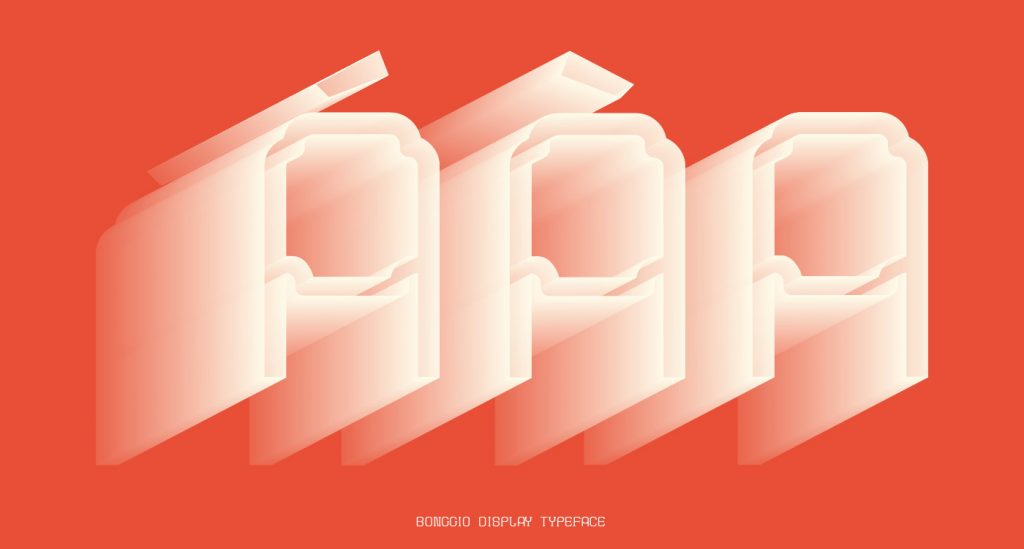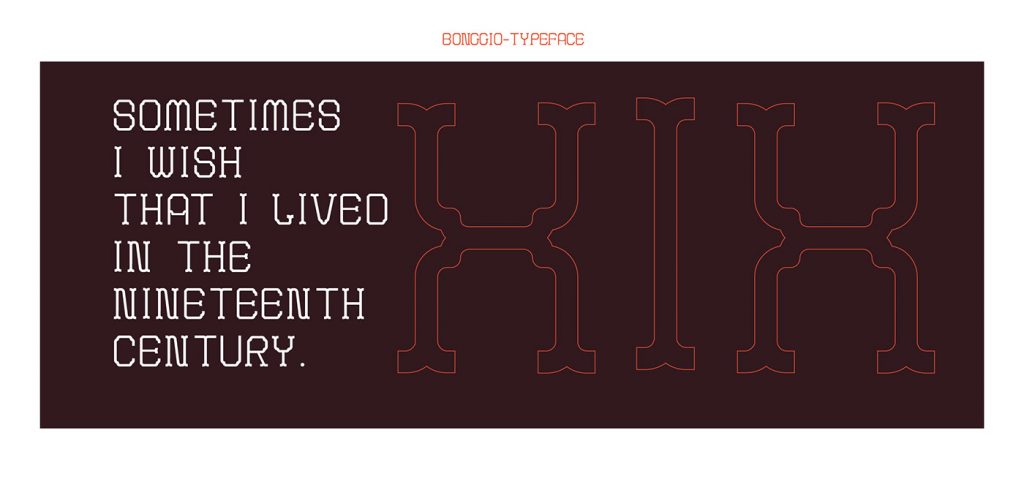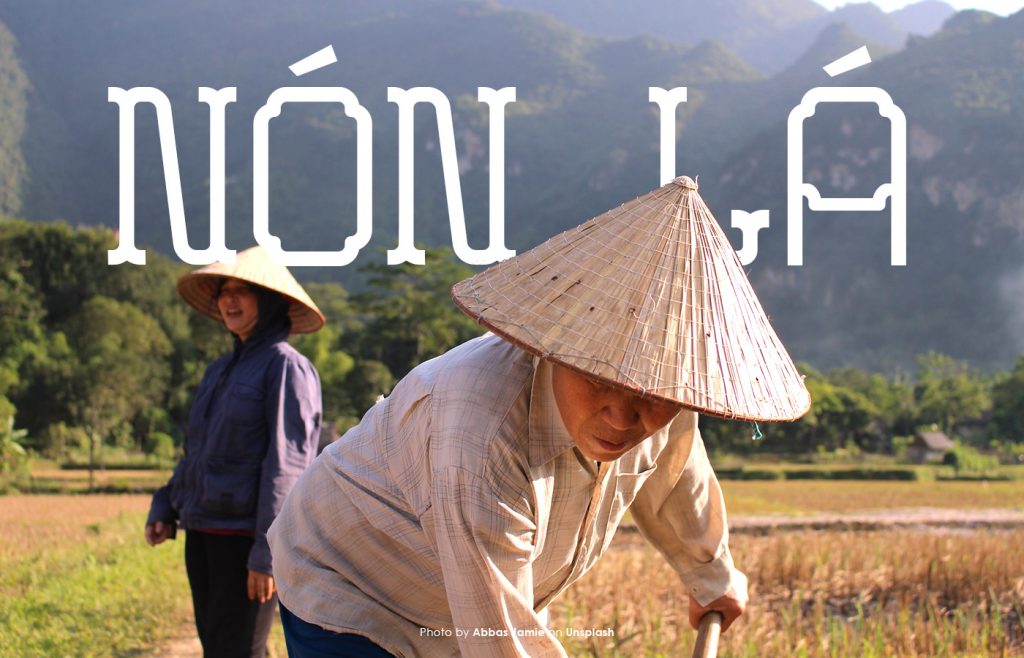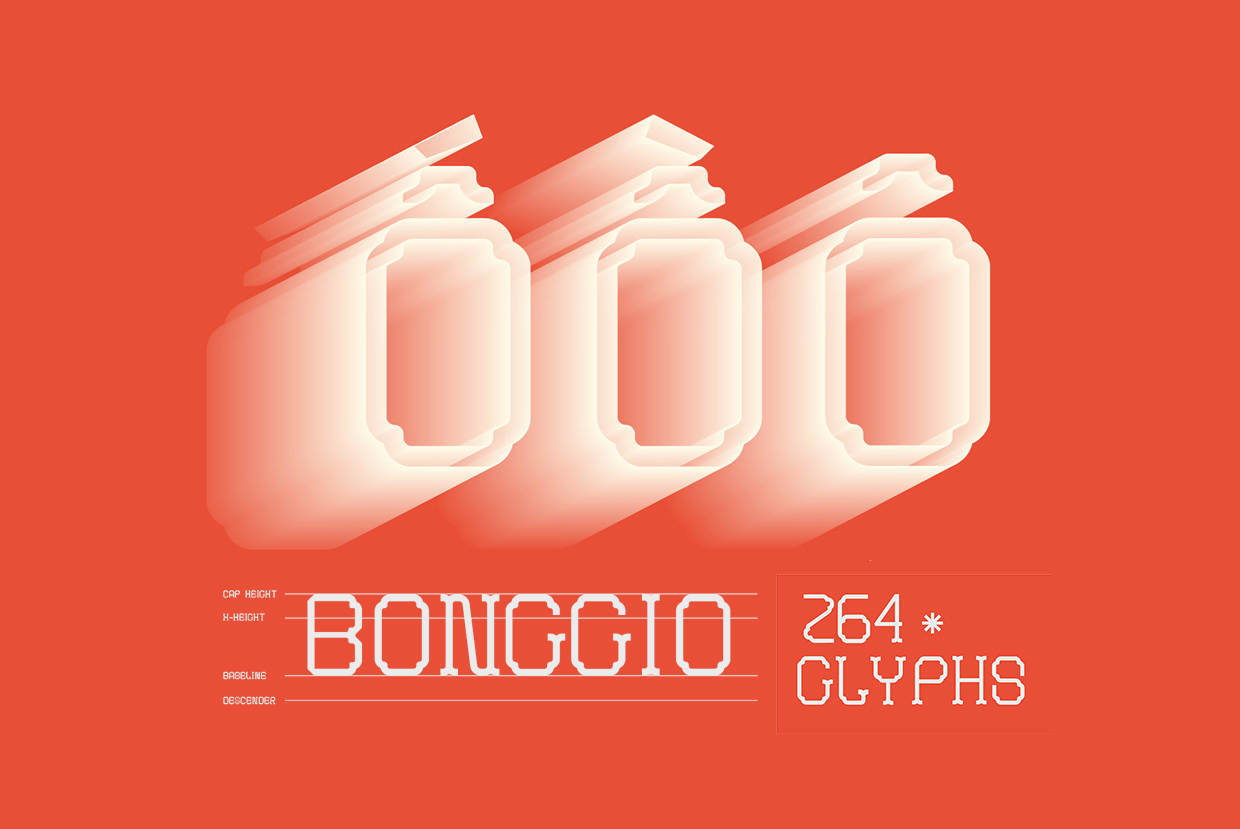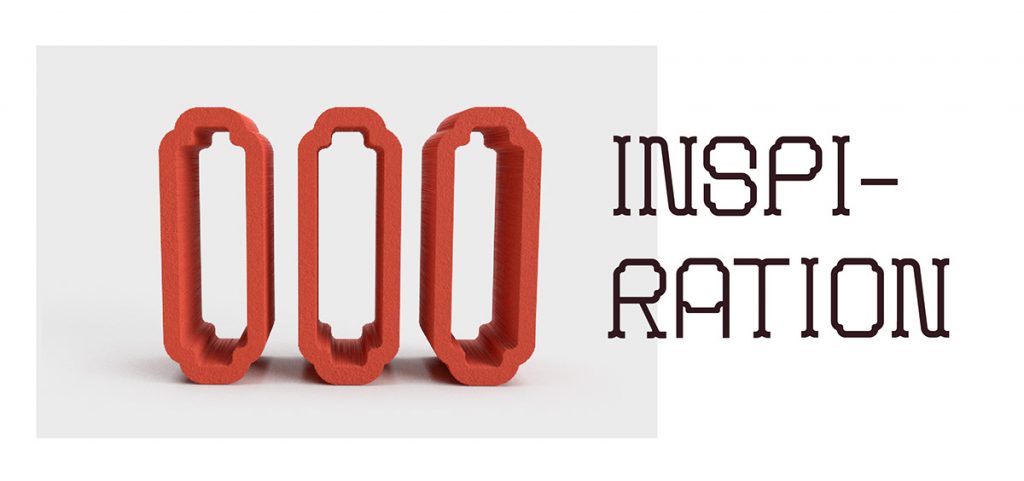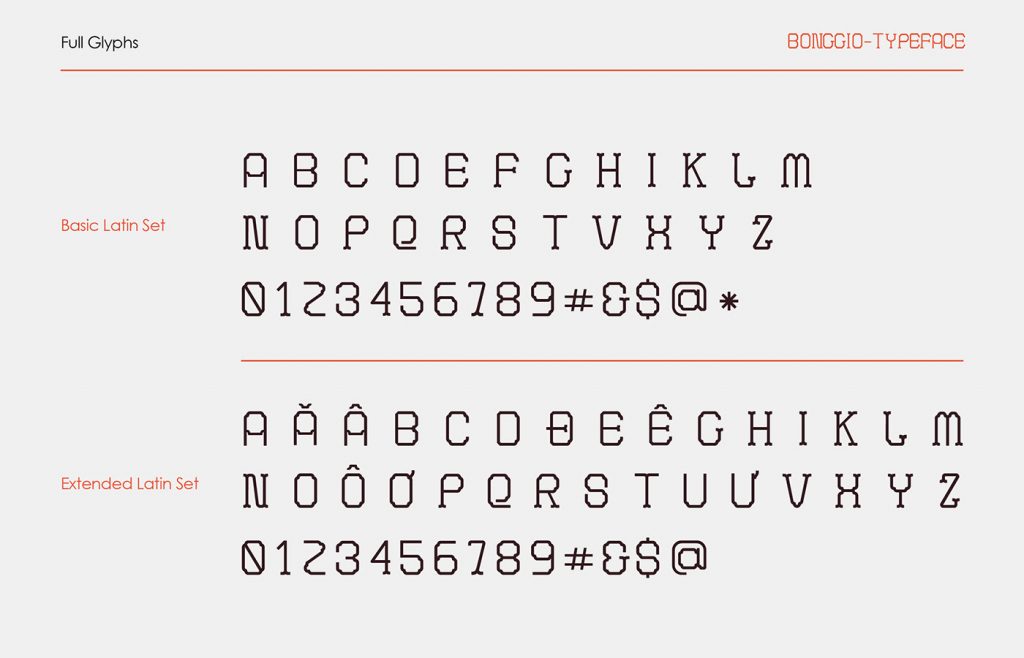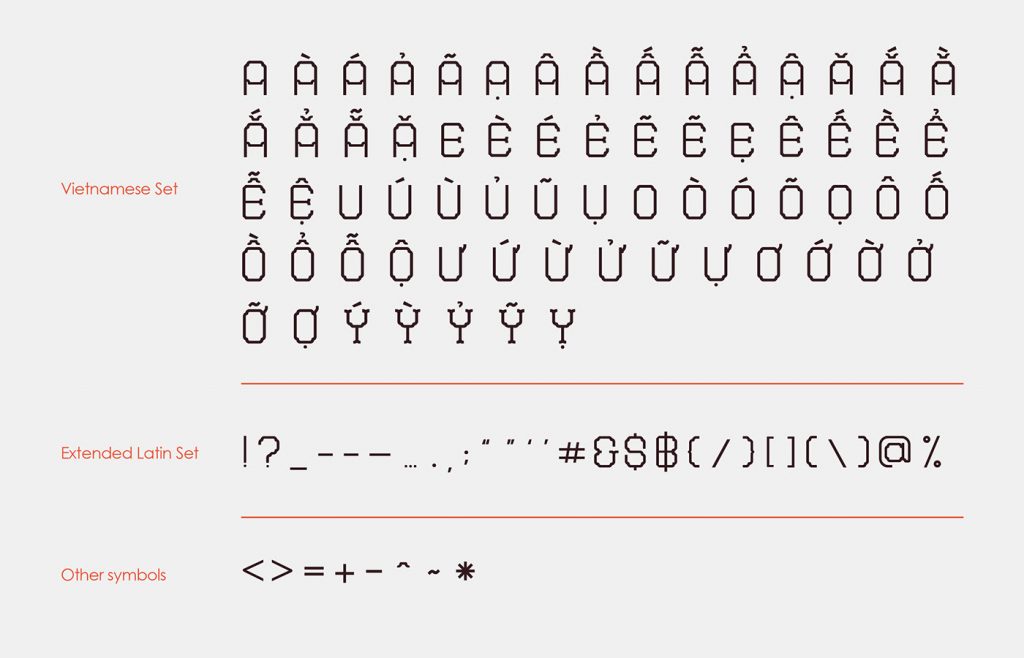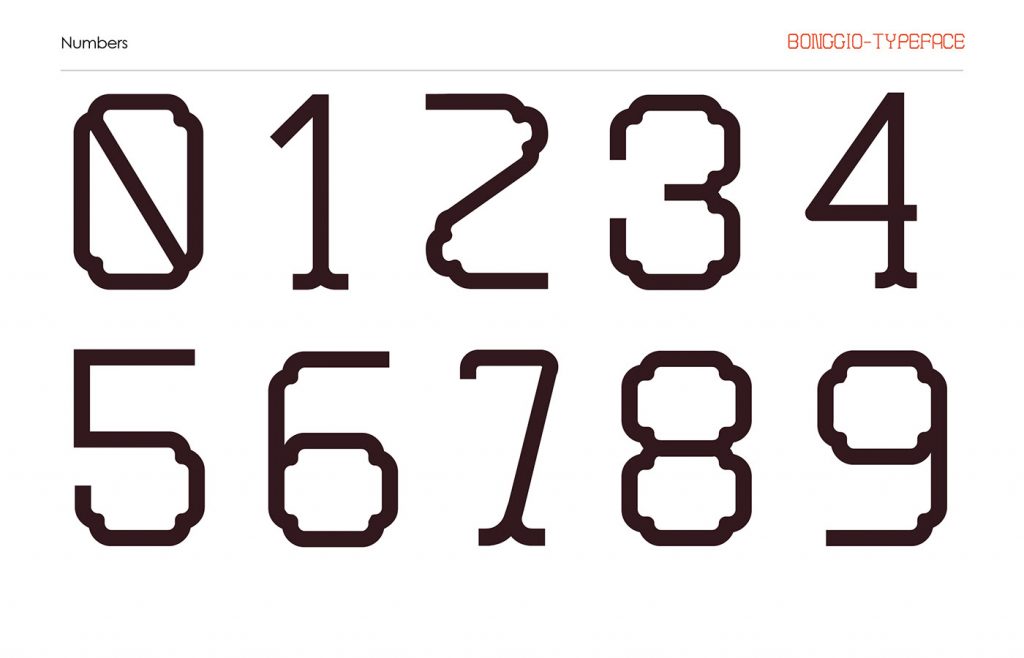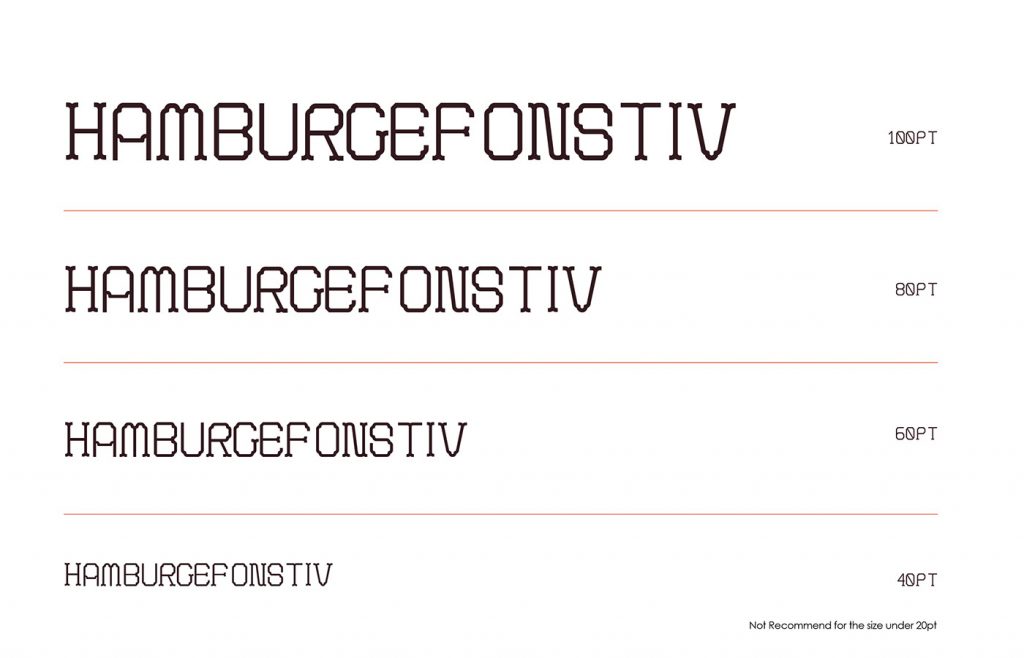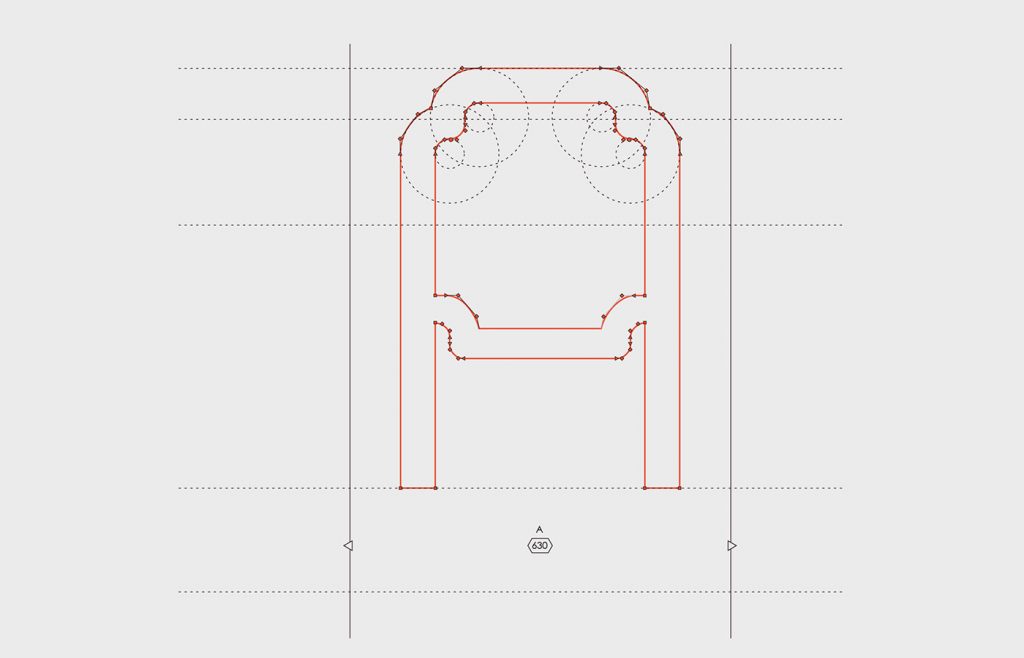
Bong Gio display là bộ font Việt do Vũ Phạm thực hiện, lấy cảm hứng từ mẫu gạch Bông Gió phổ biến ở Sài Gòn thời Pháp thuộc.
Bông Gió là loại gạch được ứng dụng vào nhiều kiến trúc của Việt Nam như tường, sàn, hàng rào với hoa văn đối xứng, cổ điển. Với mong muốn có thể tái hiện và tái hiện nét văn hóa xưa của Sài Gòn, kiểu chữ Bông Gió mang phong cách cổ điển và truyền thống.